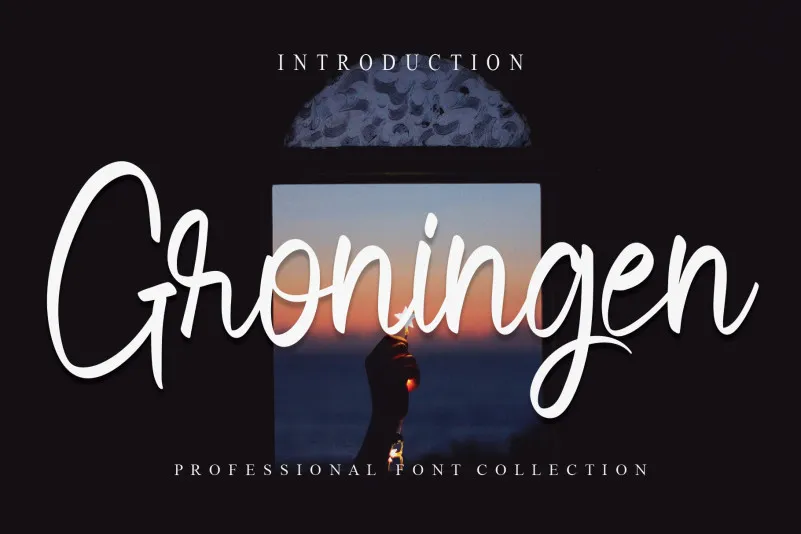
Groningen Script Font
Esta página de download apresenta a Groningen Script Font, uma elegante e delicada fónt do gênero script que traz aos seus projetos um toque sofisticado. Ideal para dar vida às histórias textuais com sutileza e charme, essa fonte é perfeita para se integrar em design gráfico profissional ou até mesmo personalizado. Inspirada em estilos de escrita artísticas, a Groningen Script oferece linhas suaves e curvas elegantes que podem ser usadas tanto no formato normal quanto em negrito. Suas letras são adaptáveis às mais diversas situações, seja para criar um design minimalista ou para adicionar profundidade e detalhes a uma página de texto. Composta por uma ampla gama de caracteres, incluindo símbolos especiais e acentos, a Groningen Script é ideal para expressar suas ideias de maneira única e atrativa. Para designers que buscam um toque especial em seus projetos, a Groningen Script Font é uma escolha perfeita. Com sua característica design script, esta fonte não apenas dá vida ao texto, mas também torna seu trabalho mais chamativo e envolvente.